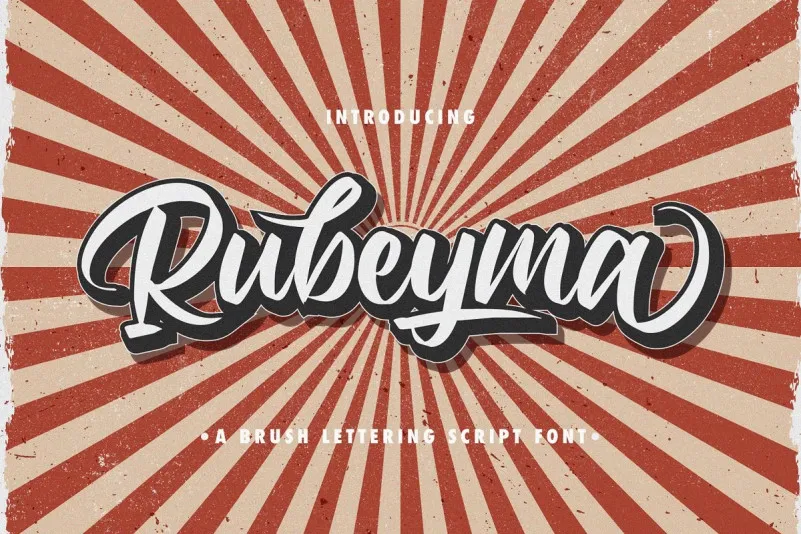
A Rubeyma Font é uma sugestão ideal para aqueles que buscam uma solução criativa para seus projetos de design gráfico. Escrevendo de forma dinâmica e elegante, essa font script destaca-se com sua aparente influência vintage. Ela foi desenvolvida pelo font designer StringLabs, caracterizada por seu formato curvo e arredondado, além da sua estética única, perfeita para dar um toque especial aos logotipos. Esta font é especialmente indicada para aqueles que procuram uma personalidade distintiva em seus materiais de identidade visual. Suas linhas fluidas e texturas vintage fazem com que ela se destaque, dando uma sensação de modernidade a qualquer design que adicione. Seja para títulos criativos ou texto detalhado, a Rubeyma Font tem o poder de transformar suas ideias mais inovadoras em trabalhos visuais vivos e únicos. Combinando elegância com um toque nostálgico, ela se destaca como uma opção perfeita para aqueles que valorizam ambientes criativos e desejam incorporar elementos distintivos aos seus materiais de identidade visual. Não deixe essa font passar em branco quando você está buscando personalizar seu design com um estilo único e moderno.